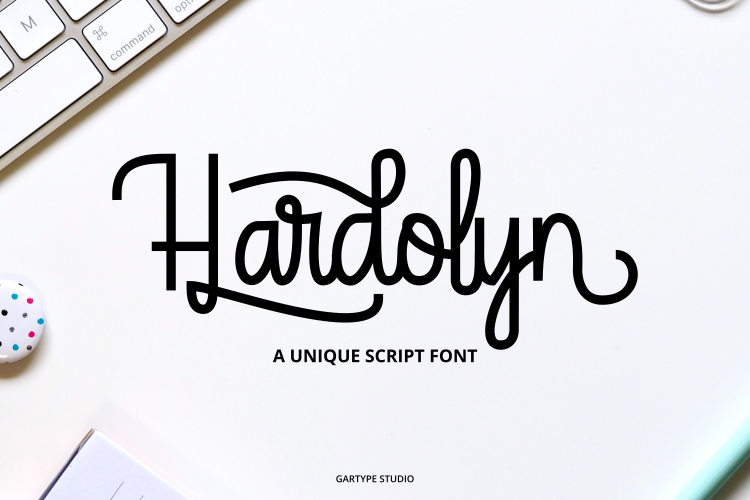
Hardolyn Script Font – Download Grátis
Descubra uma nova fonte de escrita chamada Hardolyn Script Font especialmente projetada para artistas criativos. Esta fonte única é parte da rica coleção de Gartype Studio, conhecida por criar fontes com um toque inovador e versátil. Hardolyn Script Font está preparada para se adaptar a múltiplas utilizações, adequando-se perfeitamente a texturas como citações, convites, anúncios, logotipos, posters, headlines em jornais ou revistas e até mesmo em camisas. Suavemente elegante e com um toque único, esta fonte não tem limitações, permitindo-lhe explorar suas infinitas possibilidades. Se você é parte de uma equipe que cria materiais visuais envolventes, Hardolyn Script Font pode ser a escolha perfeita para potencializar sua arte. Seja na web ou em impressão, esta fonte trará seu trabalho à um nível superior de sofisticação e originalidade. Em resumo, Hardolyn Script Font é uma adição valiosa aos seus recursos gráficos e uma ótima opção para quem busca uma fonte única que pode se adaptar a qualquer ambiente. Com certeza vai deixá-lo impressionado com suas habilidades criativas.